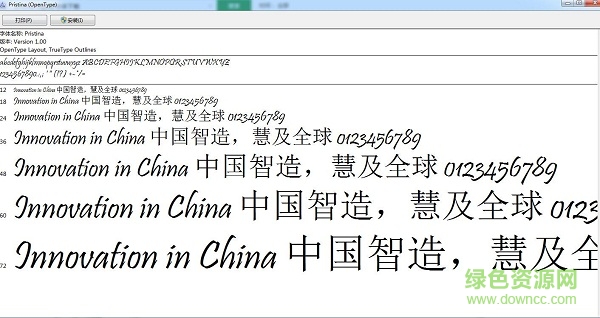
英文字體pristina regular是一款線條流暢優(yōu)美的個性字體,和中文的書法字體有點像,可廣泛應(yīng)用于廣告設(shè)計、音樂海報、游戲、網(wǎng)頁、時尚雜志等方面,小伙伴們快來下載吧!
有鮮明的節(jié)奏韻律感,色彩豐富明快,給人以生機盎然的感受。適用于女用飾品、時尚產(chǎn)品等主題。
字型設(shè)計良好,組合巧妙的文字能使人感到愉快,留下美好的印象,從而獲得良好的心理反應(yīng);
反之,則使人看后心里不愉快,視覺上難以產(chǎn)生美感,甚至?xí)層^眾拒而不看,這樣勢必難以傳達出作者想表現(xiàn)出的意圖和構(gòu)想!